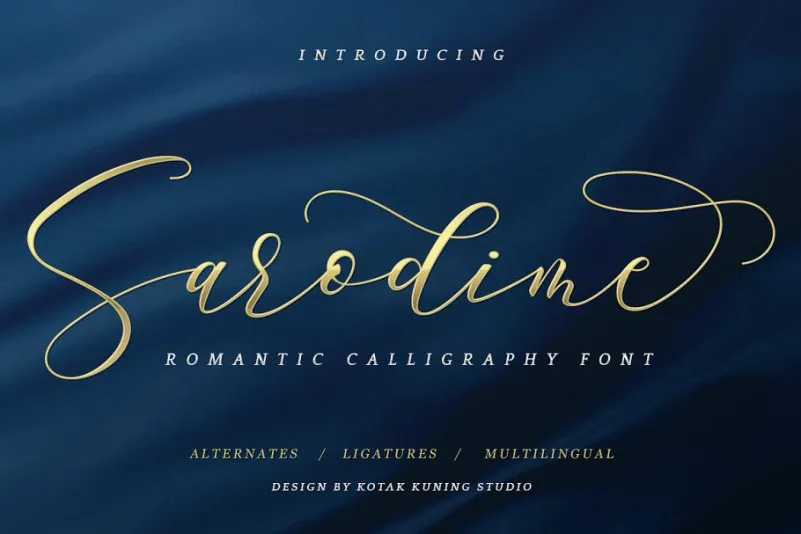
Sarodime Script é uma elegante família de fontes para projetos que valorizam a simetria do belo estilo grego. Este texto tipográfico romântico, meticulosamente criado pelo designer Hamilton, transmite um encanto e sofisticação sem igual. Esse design único foi concebido para complementar seu marca pessoal de maneira incrivelmente natural e estilosa. Ideal tanto para designers de sites quanto para pessoas que simplesmente desejam adicionar uma dose de elegância a suas mensagens digitais, Sarodime Script é uma escolha inteligente. Seu fluxo fluido cria um texto atraente e envolvente, tornando-o perfeito para criar uma identidade visual única e inovadora. Este é o tipo de font que pode transformar sua marca em algo mais chamativo e memorável, deixando uma impressão duradoura no seu público-alvo.